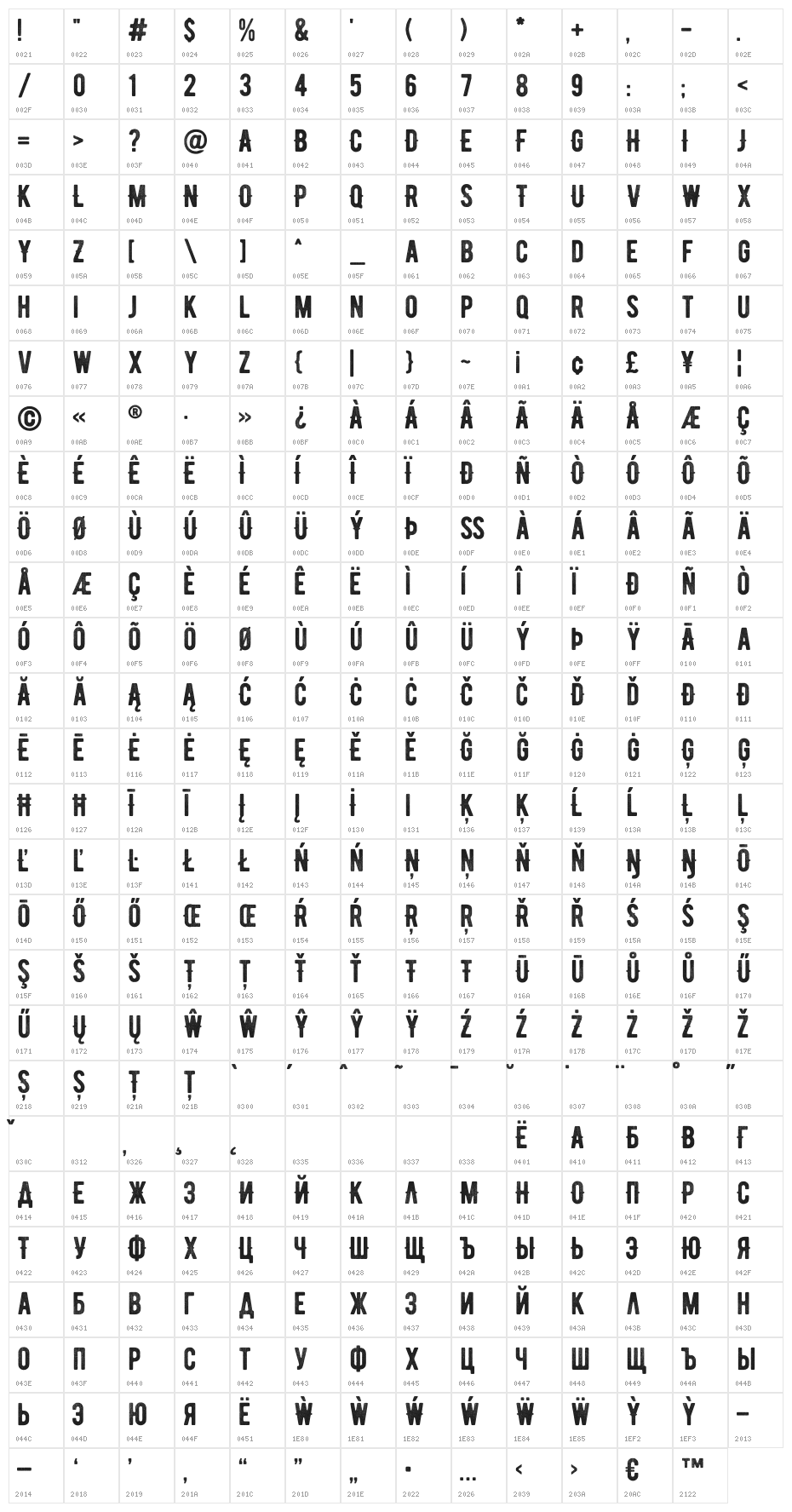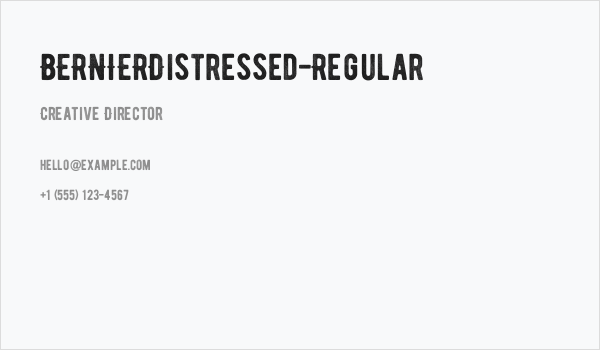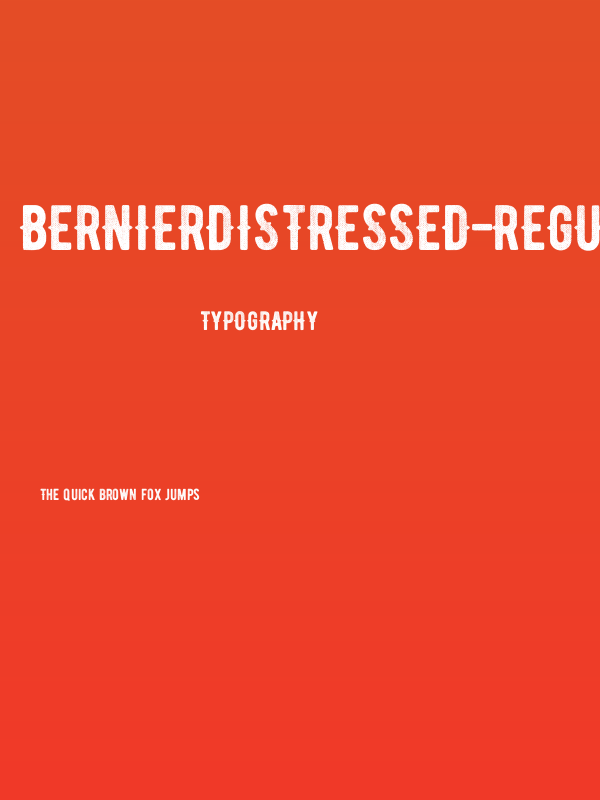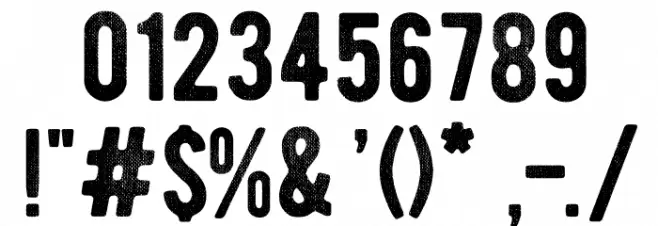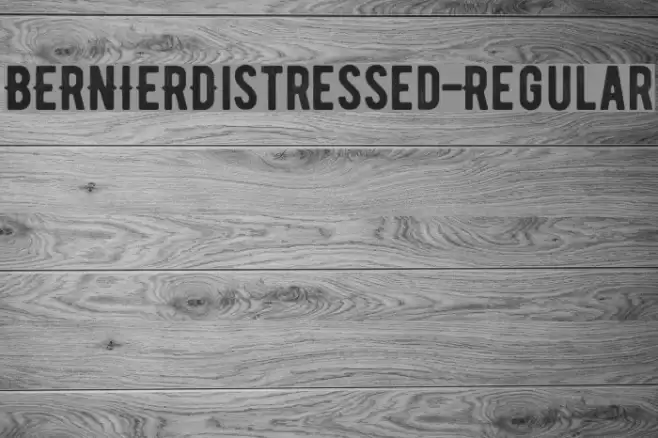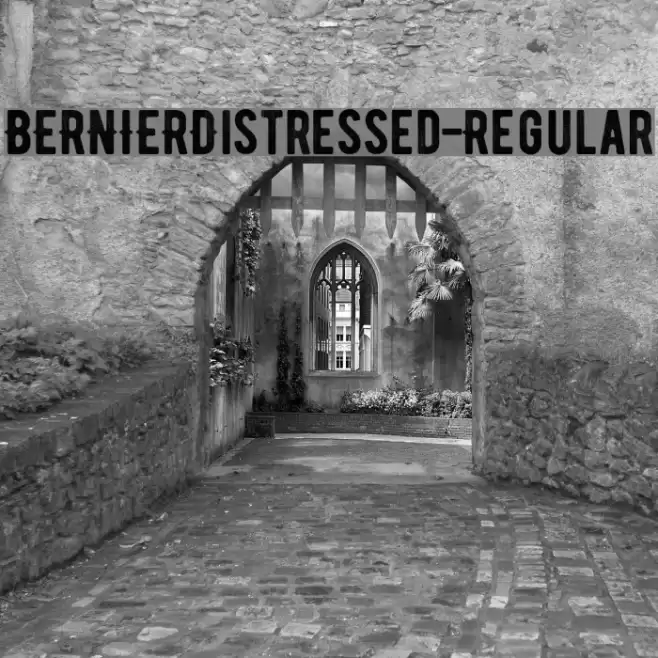
BERNIERDistressed-Regular Font
| おすすめプロジェクト | Ideal for vintage-themed posters, branding for outdoor or adventure products, and any design needing a strong, nostalgic touch. |